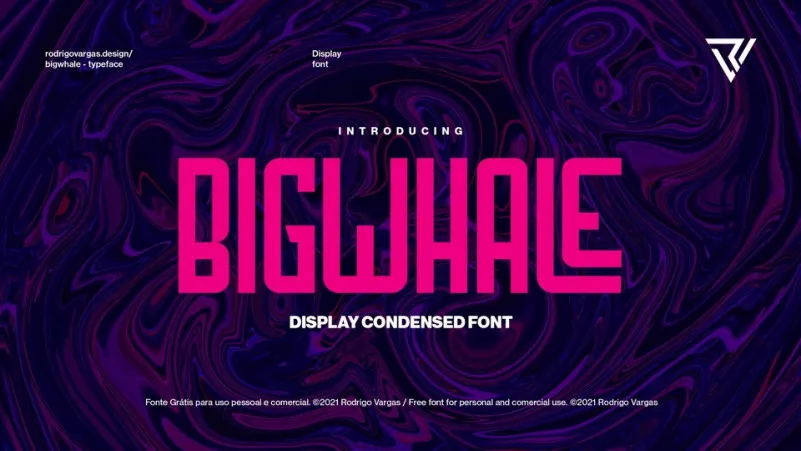
Bigwhale Display Font – Download Grátis
Esta é uma fonte de sans-serif criada para usos visuais grandiosos – seja como cabeçalhos em grandes tamanhos, elementos de marca, logotipos ou aplicações de exibição. Introduzimos um estilo moderno e único que foi projetado especificamente para headlines, textos maiores e uso visual. Este tipo é ideal para usos titulares com conjunto de números, símbolos básicos e pontuação. A letra ‘W’ ainda conta com um caracter alternativo. Além disso, o font também inclui algumas adições para alguns conjuntos de letras, facilitando ainda mais a personalização de seus designs. Uma das grandes vantagens deste tipo são as setas que acompanham os caracteres ‘Q’, ‘R’ e ‘P’. As setas ‘<<>‘ e ‘><<', em especial, permitem flexibilidade no uso da fonte. Além disso, o designer também incluiu um conjunto de símbolos únicos para complementar a fonte. Para usuários que adoram fazer sua própria marca e criarem elementos visuais personalizados com grande destaque, esta é uma excelente opção. Com a 'Bigwhale Display Font', você terá tudo o que precisa para transformar qualquer projeto em algo visualmente impressionante.